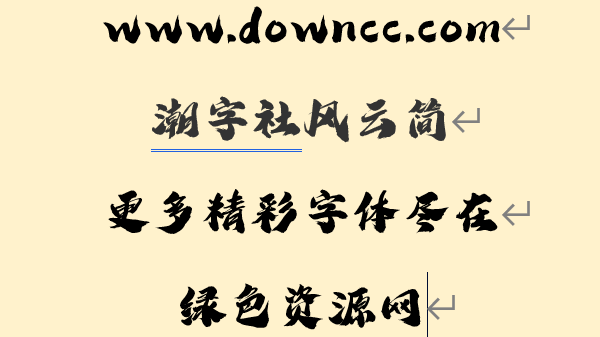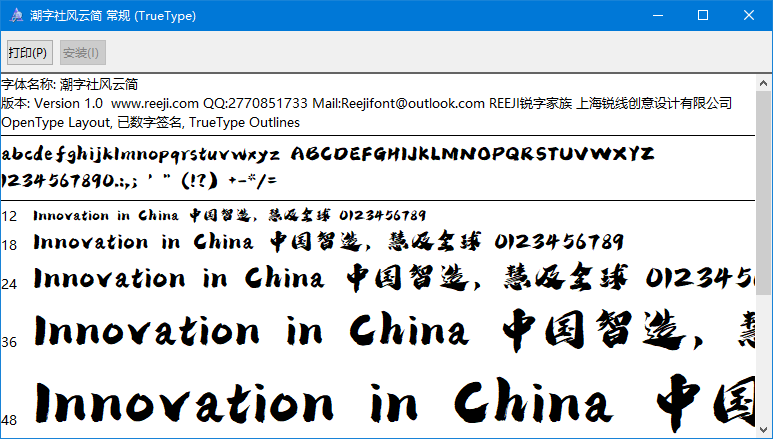
潮字社風(fēng)云簡(jiǎn).ttf字體是一款出自潮字社字庫的中文簡(jiǎn)體字文件。該字體將書法感和設(shè)計(jì)融為一體,整體效果非常出色,擁有不錯(cuò)的視覺效果。有喜歡的朋友,可以將其應(yīng)用于信息展示的場(chǎng)合使用
1、行間距比較寬,適合做封面
2、毛筆字體,手筆有頓
3、筆鋒偏柔,更加大氣